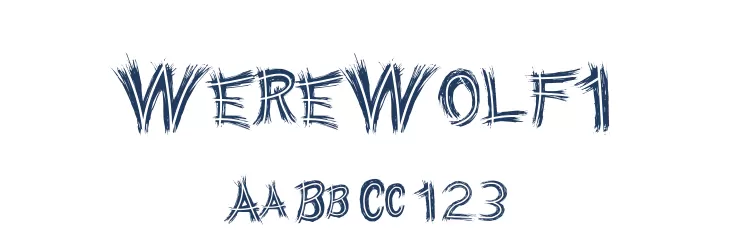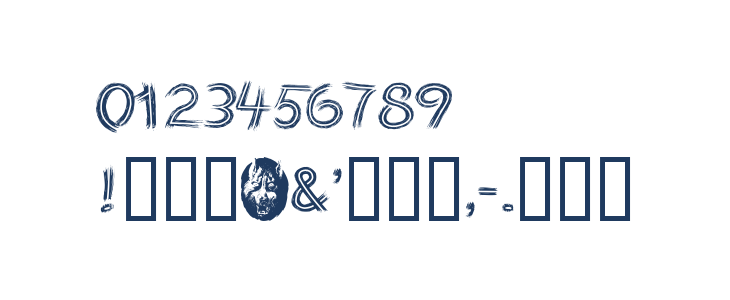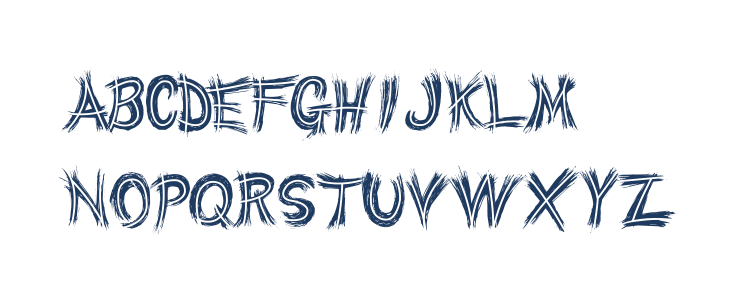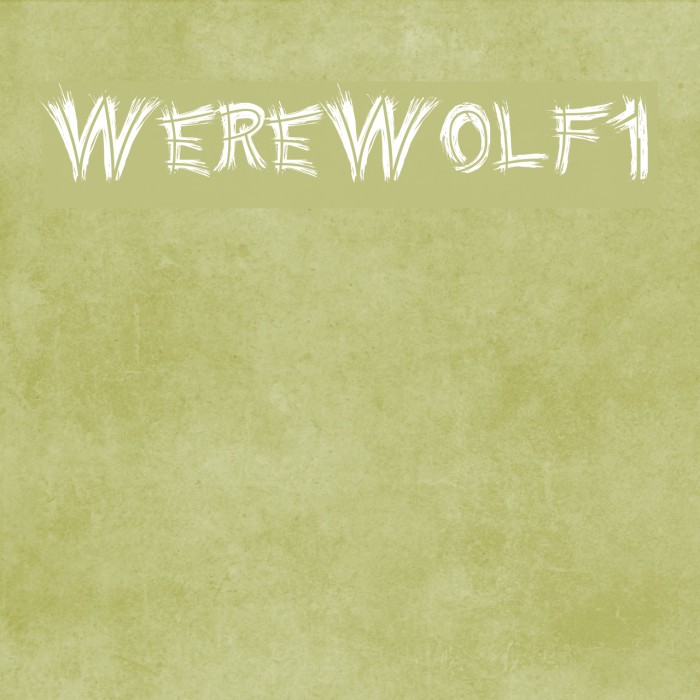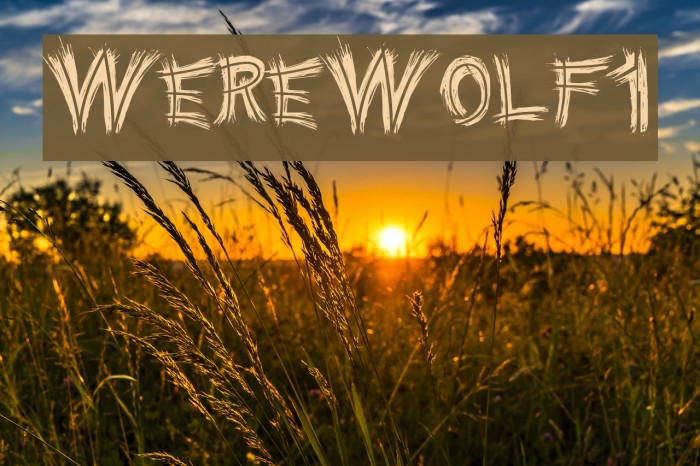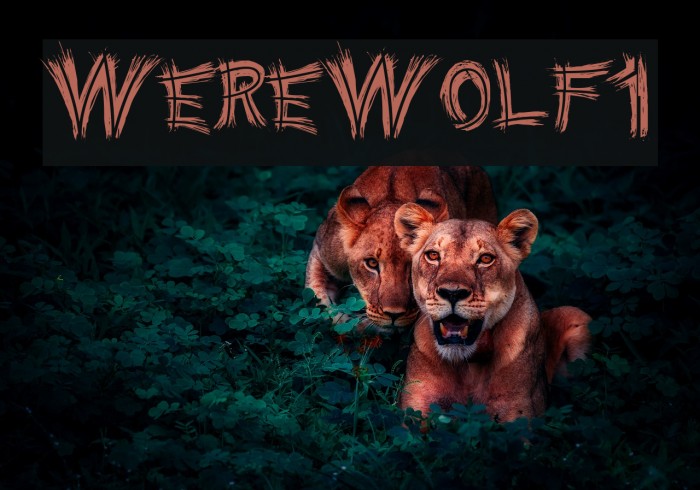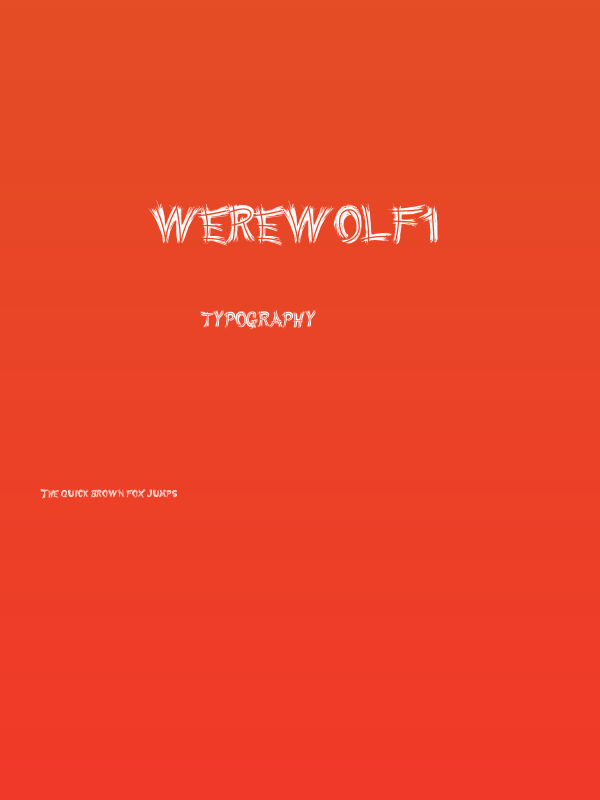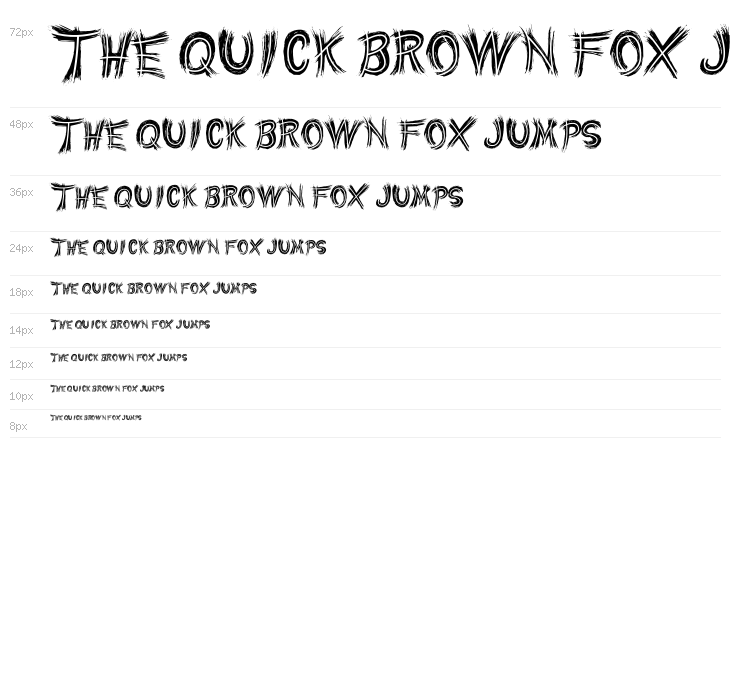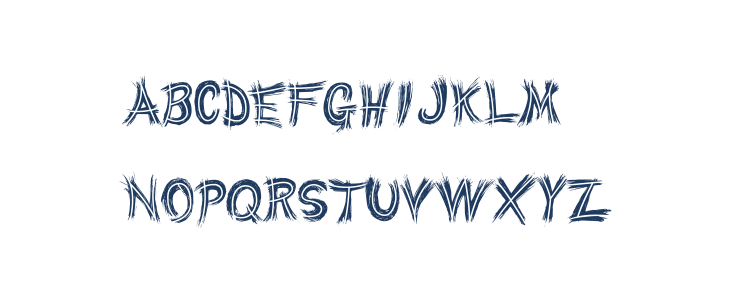
WereWolf1 Font
| مشاريع مقترحة | Ideal for horror-themed designs, Halloween promotions, edgy branding, and creative projects requiring a wild, unpredictable look. |